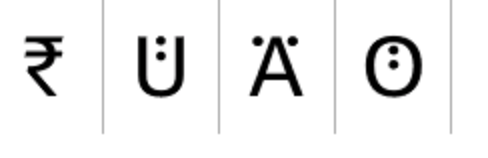
Etiketten für Schlüssel; 4mm Höhe; Majuskeln; Umlaute in gleicher Höhe
Freunde aus einem Verein baten mich, eine Taxonomie für eine größere Zahl an Schlüsseln zu entwickeln und dann die Schlüssel zu etikettieren (nicht die Schlüsselanhänger).
Die bedruckbare Höhe des Etikettenbandes beträgt 4 mm, die Breite ca. 15 mm.
Die Gespräche ergaben, dass eine zweitstufige Hierachie ausreicht:
Zwei Majuskeln, eine Ziffer. Beispiel: GB 2
Die Details dazu sollen hier keine Rolle spielen.
Da auch für sehschwache Nutzer die Etiketten so gut wie möglich lesbar sein sollen, war meine Überlegung, die 4 mm volständig mit Majuskeln auszufüllen.
Es sollen jedoch auch Umlaute vorkommen.
Gibt es Fonts, wo die Punkte der Umlaute die Oberkante der Nicht-Umlaute nicht überragen?
Zur "FF Bauer Grotesk":
werden bei der Eingabe eines Umlautes die Punkte über der Oberkante der Majuskeln gezeigt.
Die Zeichen sind heute in der Regel als OpenType-Variante hinterlegt.
Ansonsten lässt sich das in einem Vektorgrafikprogramm ja auch leicht selbst für jeden beliebigen Font bauen.
Was muss man denn bitte im Textfeld für die Beispieltexte auf den Webseiten der Font-Anbieter eingeben, damit man den Titelsatz-Umlaut ansehen kann?
"Graublau Sans Pro" habe ich mir auf https://www.myfonts.com/fonts/fdi/graublau-sans-pro/ angesehen. Es gibt in dem Auswahlmenü die Option "Titling". Aber auch damit wird kein Titelsatz-Umlaut angezeigt.
Die Cormorant auf der Liste ist übrigens frei (und exzellent ausgebaut, und einer meiner persönlichen Lieblinge...) -- aber für eine solche Beschriftungsaufgabe würde sie mir jetzt zugegebenermaßen auch nicht als erste einfallen.
Obwohl: Die „gemäßigteren“ Buchstabenformen, und einer der fetteren Schnitte -- hmmm...
Im Zweifel die Glyphentabelle bemühen.
Wenn es zugehöriges OpenType-Feature gibt, wird das dort auch angezeigt. Ansonsten spricht man das Zeichen in OpenType-fähigen Programmen über die Glyphenpalette der Anwendung an.
Die Titelsatzumlaute sind dort übrigens als kleine Es ausgeführt und werden per ss04 angesprochen.
Die Cormorant mit ihren starken Unterschieden in den Strichstärken finde ich für den hier beschrieben Zweck (4 mm bedruckbare Höhe, Lesbarkeit auch für Sehschwache so gut wie möglich gewährleisten und die schwache Auflösung) nicht so passend.
Die EspressoDolce hat mir eine zu geringe Strichstärke - im Vergleich zu denen von z.B. der Graublau.
Da im Verein verschiedene Leute die Exceltabelle mit den IDs für die Schlüssel bearbeiten werden, ist es wohl keine gute Idee für die Umlaute "besondere Eingabeverfahren" einzusetzen. Ich habe mich zum Verzicht entschieden.
Aber auf Titelsatz-Umlaute werde ich bestimmt nochmal selber zugreifen. Eine interessante Bereicherung.
Geworden ist es jetzt der Font "Lato Black" (und bei Umlauten Minuskeln). Hat ein paar verspielte Rundungen, das könnte den Benutzern gefallen, vermute ich. Und die Schrift hat sehr dicke Strichstärken.
Interessant war für mich, dass bei sehr vielen Fonts die Minuskeln von Umlauten mit den Tüdelchen über die Oberkante der Majuskeln ragen - und somit ausschieden.
Die Lato ist sicher eine gute Wahl (wenn du mit den Minuskel-Umlauten leben kannst).